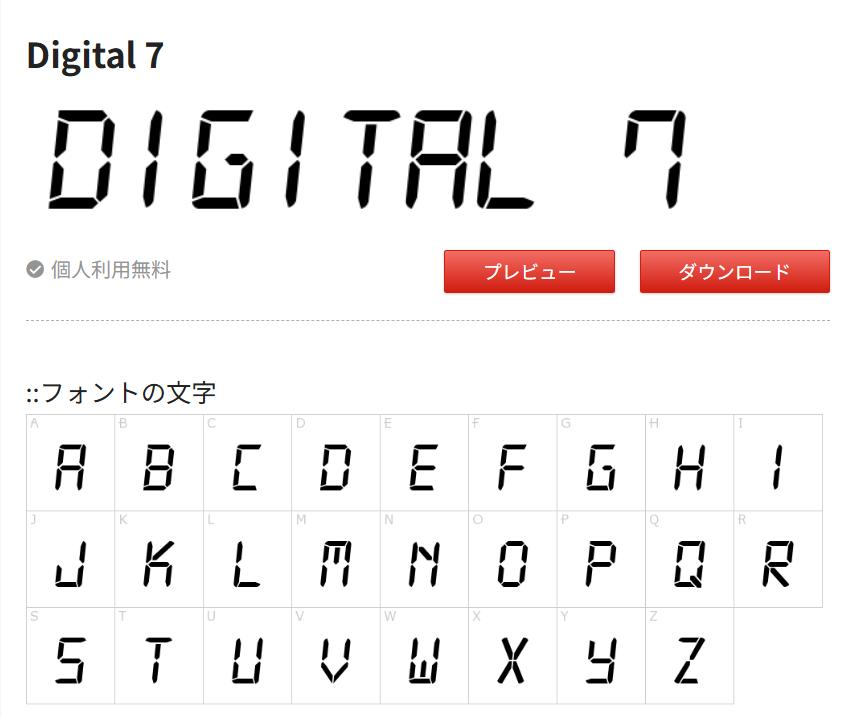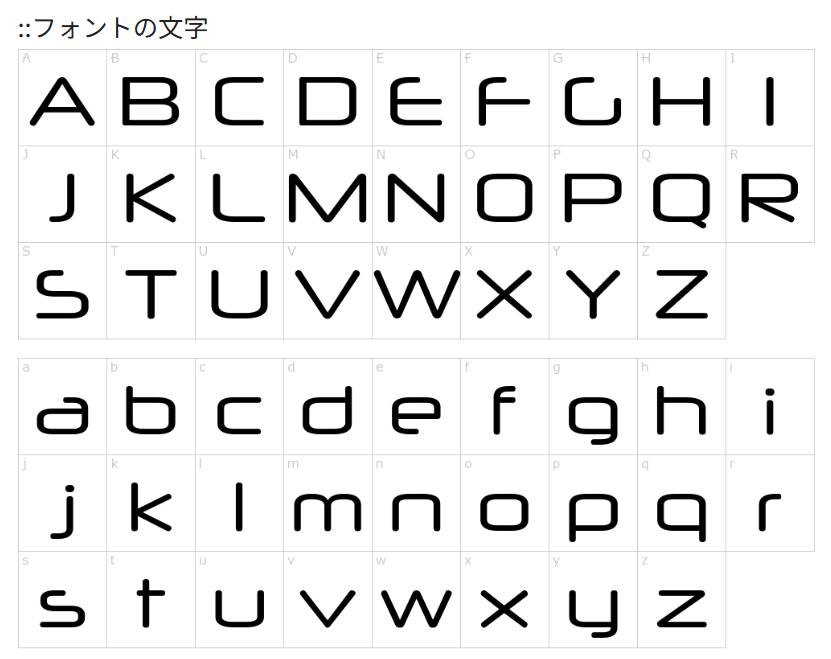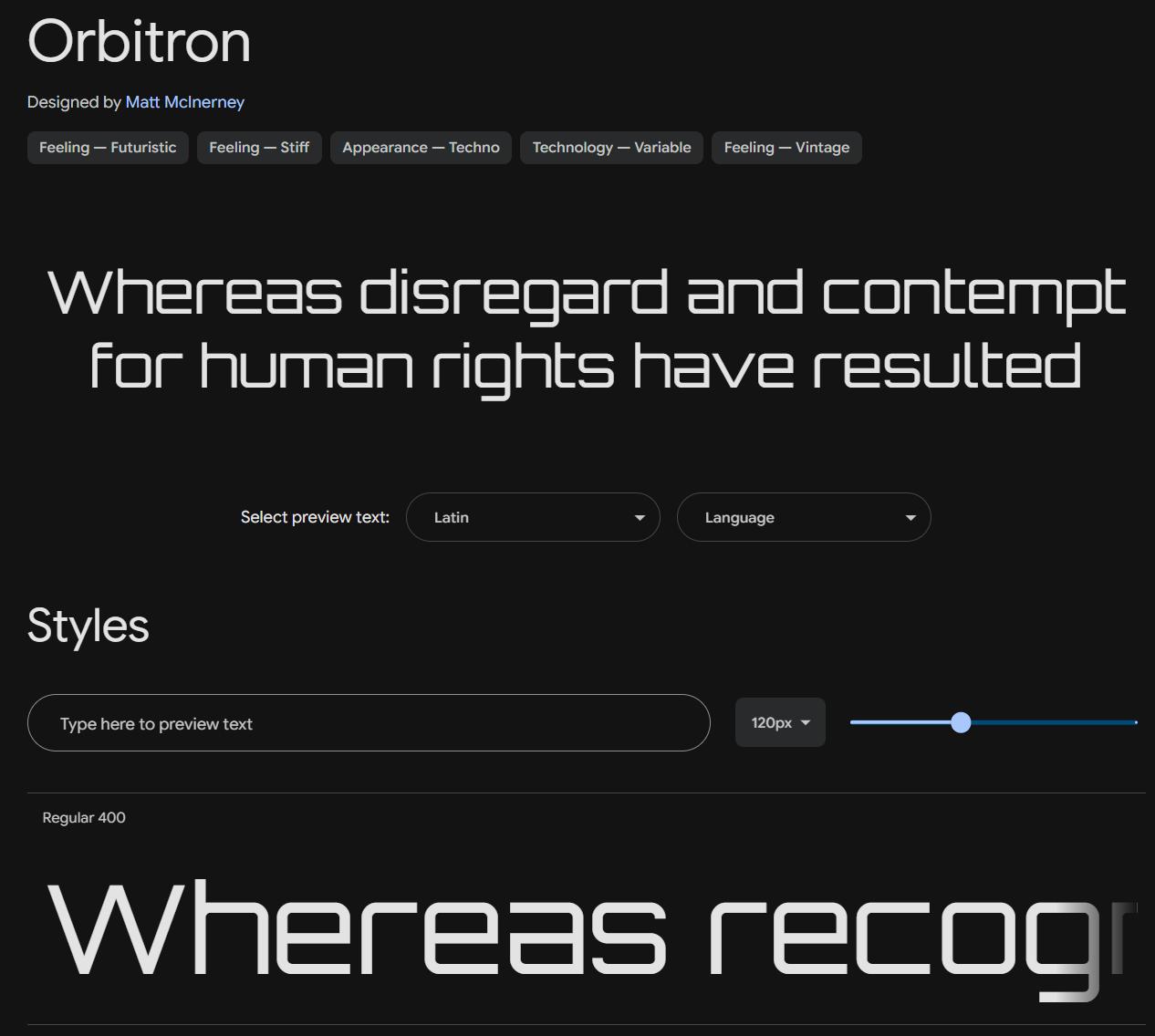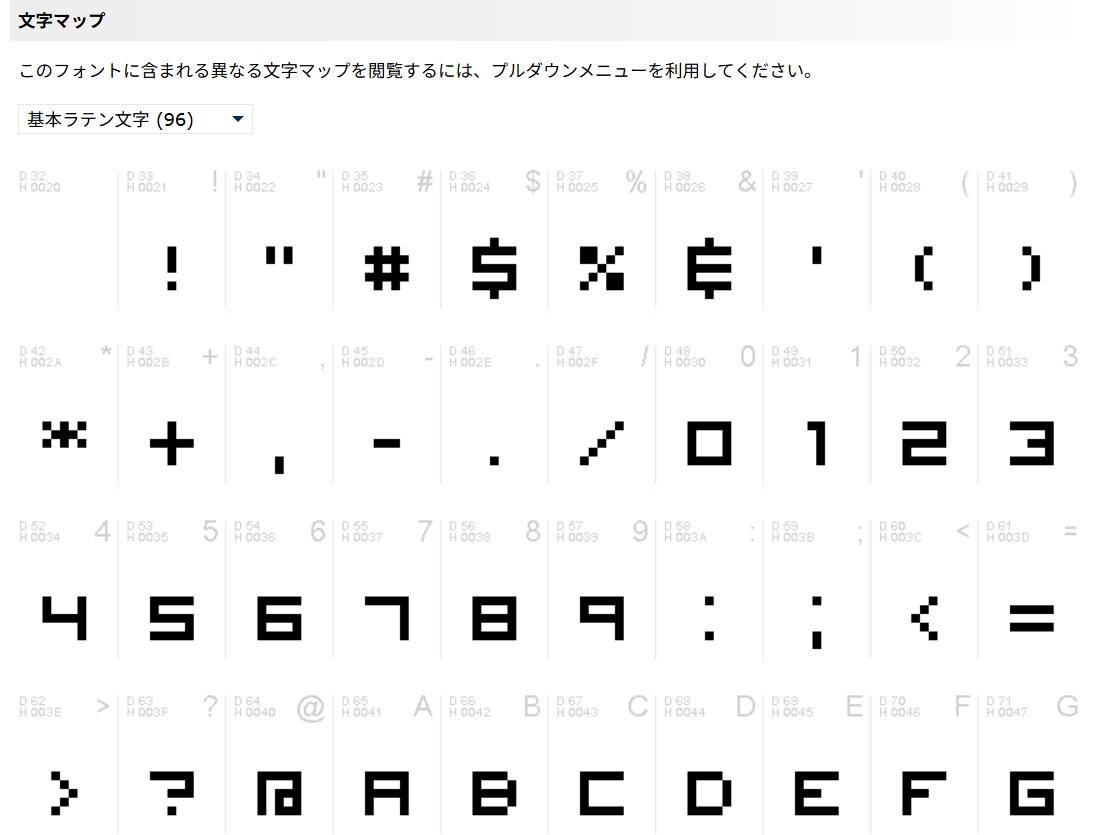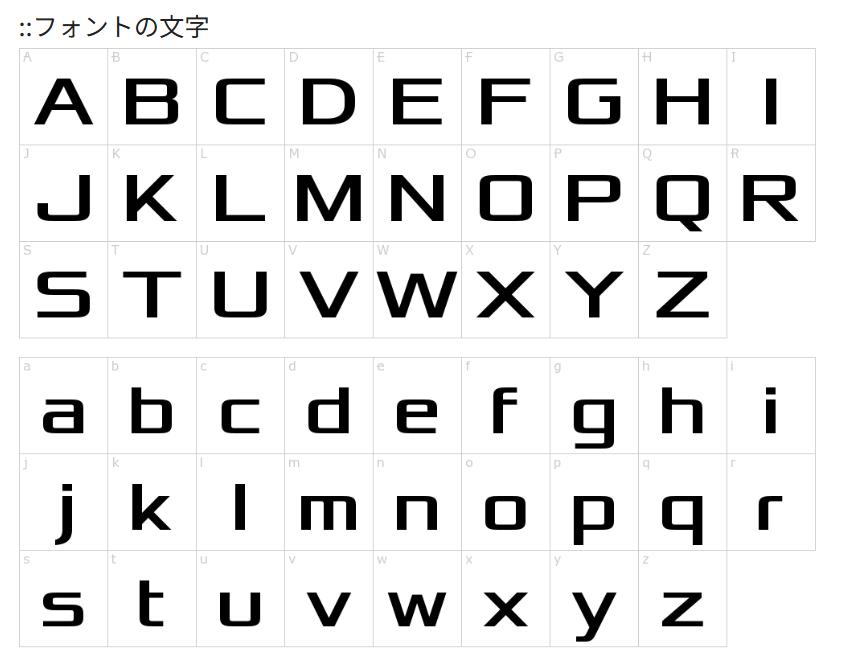
デザインにデジタル表示や近未来の雰囲気、サイバー感を演出したいときに便利なのが『デジタル風フォント』。動画のタイトルやポスター、ゲーム画面のUIなどでよく使われており、印象的なビジュアルを簡単に作ることができます。この記事では、無料で利用できるおすすめのデジタル風フォント5選をピックアップしてご紹介します。商用利用の可否や、特徴・活用例などもあわせて解説します!
「デジタル風フォント」とは、以下のような特徴を持つフォントを指します。
・デジタル時計や電光掲示板のような、ドットやセグメント表示を模した書体
・サイバー・未来的・SF風なデザイン
・エッジが効いた直線的なデザインや、無機質な印象を持つ文字形
こうしたフォントは、テクノロジー系コンテンツやゲームデザイン、YouTubeのオープニング映像などに非常によく使われています。
特徴:まさにデジタル時計風の代表的なセグメントフォント。文字が「7セグメント」で構成されていて、視覚的に強いインパクトがあります。
使い道:タイマー風テキスト、工場・ロボット系映像、スポーツ系カウント表示などに最適。
・特徴:未来的かつ幾何学的な形状が魅力。曲線が少なく直線的で、サイバー系の雰囲気を演出できます。
・使い道:テクノロジー系ロゴ、UIデザイン、近未来映画のタイトル風表現。
・特徴:レトロゲーム感あふれるピクセルスタイルのフォント。低解像度時代のPCやゲーム機のような表示が再現できます。
・使い道:レトロゲーム、ドット絵風の作品、8bit風の映像制作。
・特徴:洗練されたSF風フォント。高級感のある曲線と直線を併せ持ち、宇宙や近未来のイメージにぴったり。
・使い道:宇宙モチーフ、テクノロジー製品のパッケージ、Web UI。
・特徴:独特の横長の文字幅が特徴で、個性的かつスタイリッシュな印象を与えます。サイバー映画のタイトルにも似合う。
・使い道:音楽アートワーク、YouTubeチャンネルロゴ、ハイテク系広告。
デジタル風フォントを使うときは、以下のポイントを意識するとデザインが引き立ちます。
・暗めの背景+明るいフォントカラーで、未来感アップ(例:黒背景にシアン、緑、白など)
・文字にグロー効果やネオン風エフェクトを加えると、よりサイバーで映える
・単体で使うよりも、英数字中心の短い文字列(例:「START」「SYSTEM ONLINE」など)にすると効果的
・日本語には対応していない場合も多いため、英語や記号の活用をメインに